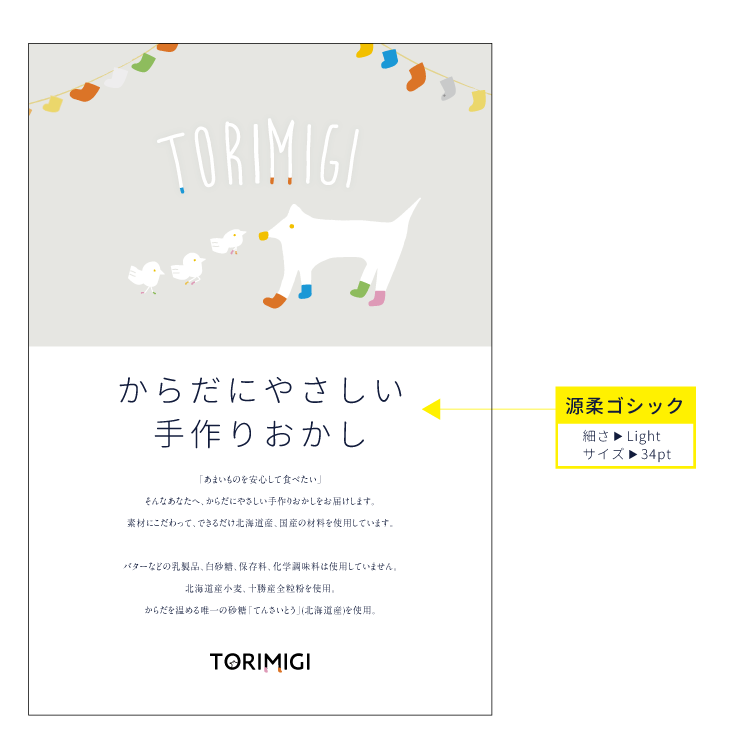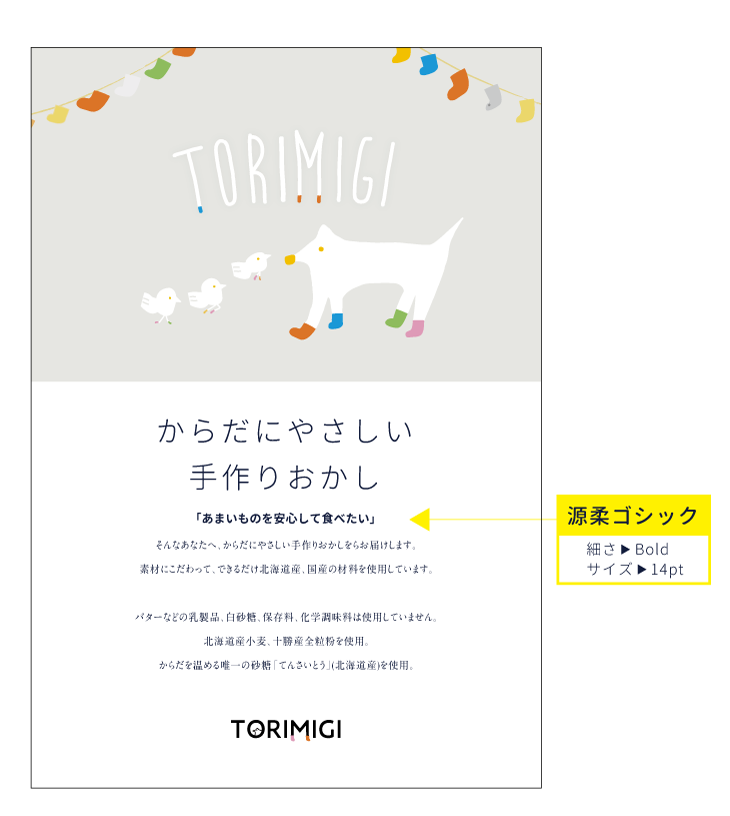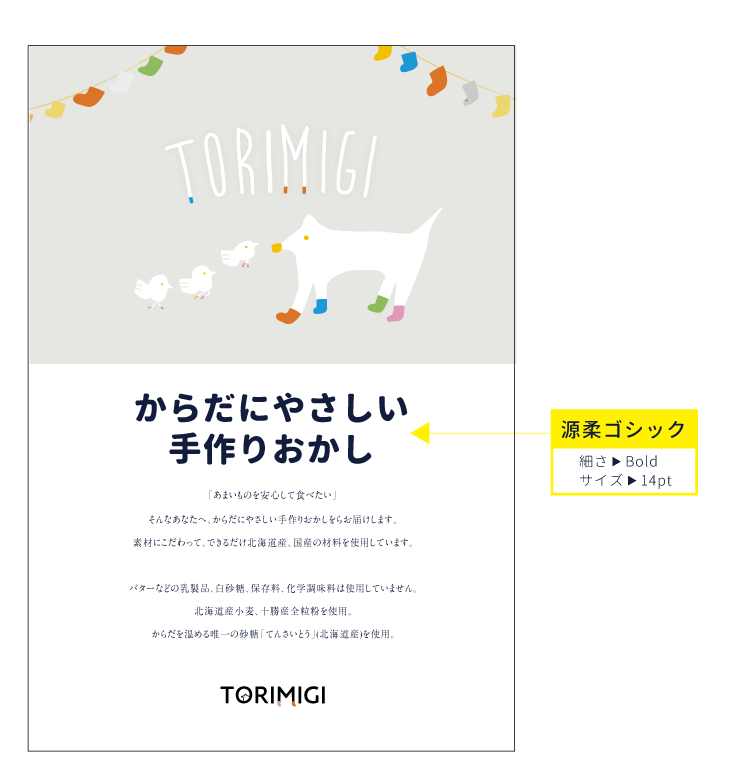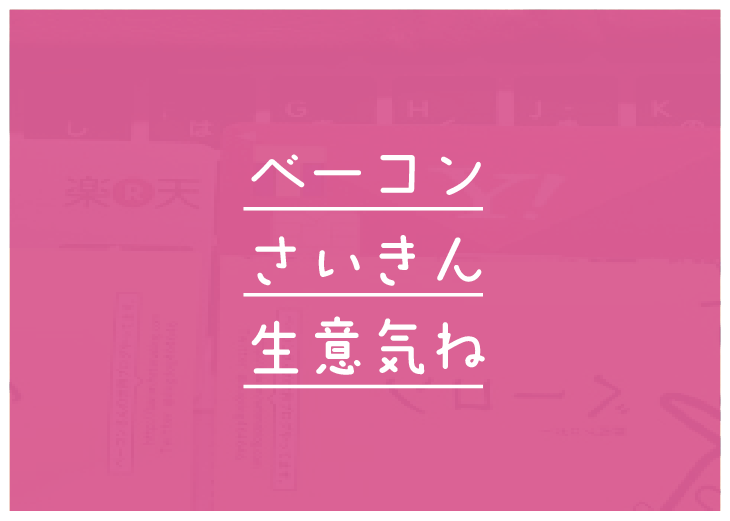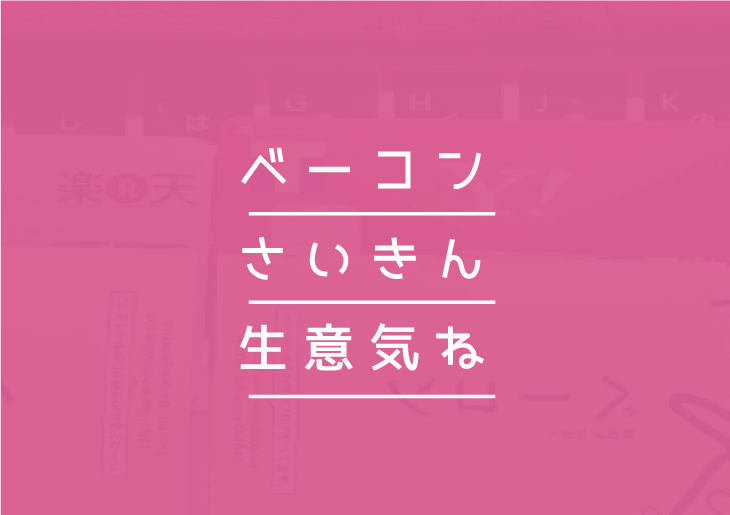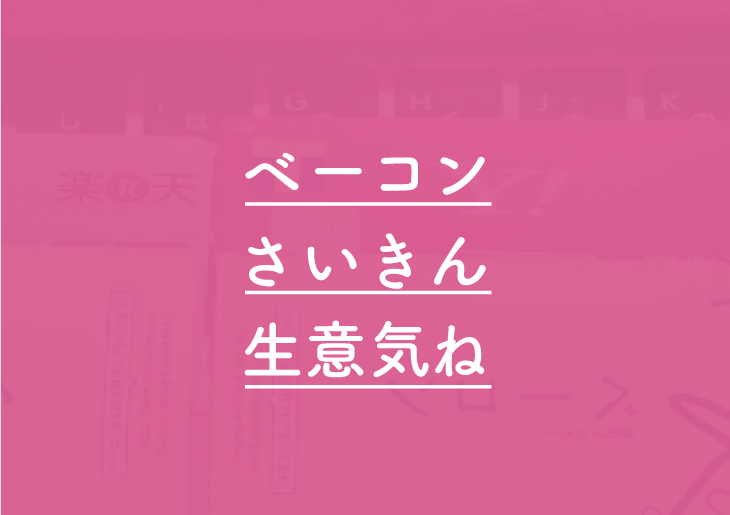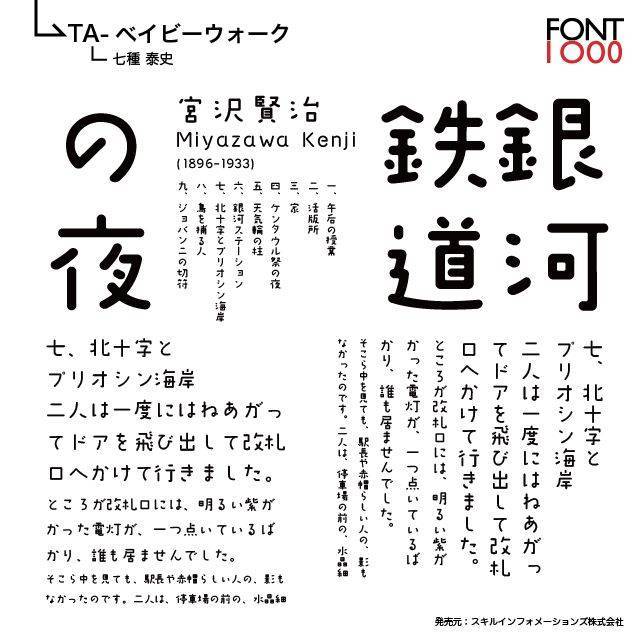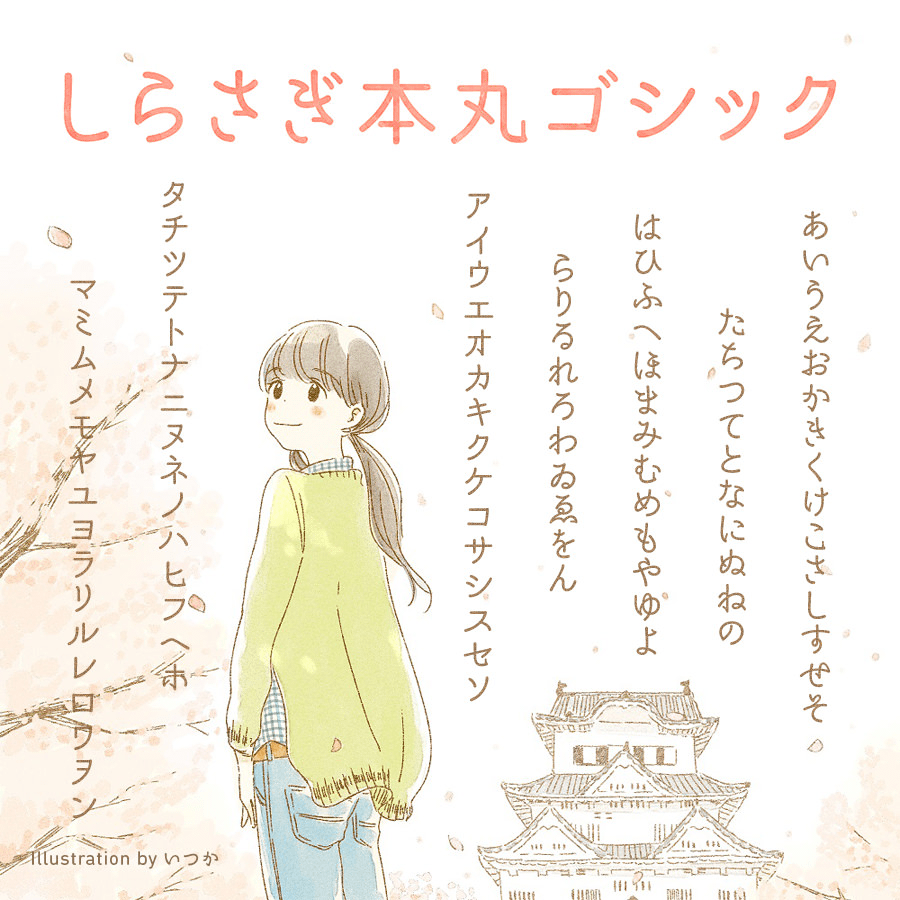
デザイナーのベーコンです
ぼくが普段仕事で使っている、かわいいフォントを紹介します!
どれもデザイン仕事で頼りになる!やつですけど、フォントを選んだ基準はこの2つです
・仕事で使える!
・仕事では使いづらいけどものすごい好き!
どんな場面で使うと上手に使えるのか、デザイナーの目線で解説していきますね!
このルールで行きます!
仕事で頼りにしてる「かわいいフォント」まとめたよ!
①〜④ 有料フォント
1.やまフォント(日本語フリーフォント)
文字の太さがそれぞれバラバラなフォントです、まるで子供の字みたい。
と、、それだけじゃないんです!
こういうような、子供の字のようなフォントって意外とありますが、その中でも飛び抜けていると思うんです。
その理由はこの3つ
1.文字が太いのでタイトルにも使いやすい
2.漢字がある
3.美しいバランス
解説していきます。
1.文字が太いのでタイトルにも使いやすい
子供の字のようなフォントは他にもあるけど、細いものが多いんです。
やまフォントは太いので、タイトルにも使いやすいですね。
2.漢字がある
漢字がないひらがな、かたかなだけのフォントも多いです。
やまフォントは漢字もあります。
3.美しいバランス
やまフォントは文字の太さはバラバラだけど、一つ一つの文字が美しいんです。
明らかにアナログで書かれたアンバランスさが絶妙に気持ちいいのフォントなんです。
やまフォントで作ってみました!
メインのタイトルはやまフォントです。
文字はくずさず、テクスチャなどを入れてみました
使える場面
・商品パッケージ、ポスター・チラシのタイトルに使えます。
・子供の書いた文字を表現する時
・アート感をだしたいとき(美術館のポスターとか)
やまフォントまとめ
下手くそだけど愛しくてたまらないやまフォントの紹介でした。
こういうフォント(文字)好きすぎる。
ポイントは、手書きっぽいけどちゃんとデザインされていることです。この場合は、背景が全面青いことにより「デザインされてる感」が感じられますね
この文字のくずし方も、やまフォントに通じるものがあるよね
美しいなあ
と、ぼくも似たような印象のデザインを、やまフォントで作ってみました!
次は普通の可愛い丸ゴシック?!
いやいや、ただの丸ゴシックじゃないんだよ。
2.源柔ゴシック (げんじゅうゴシック) 日本語フリーフォント
はい、来ました!
一見ただの丸ゴシックですよね。
これの良さが分かる人は、デザイン通だと思います。
このフォントの良さ、ずばり言いますと太さの種類が多いこと、コレとっても大事なことです。
・太さが多いので、様々な表現ができる
非デザイナーほど使ってほしいフォント
デザインを始めたばかりの人や非デザイナーの人が作るデザインって、なにが大事かはっきりさせていないことが多いんです
デザインとは
大事なものに順番をつけて、表現すること
とも言えるんです
つまり、
・大事なこと
・その次に大事なこと
・補足的な表現として伝えるべきこと
これらを整理して表現するのがデザインの大事なポイントなんです。
それを学ぶ前にデザインを作ると大抵こうなります
これも、これも、、これも、ぜんぶだいじ!!!!!!
ごちゃごちゃで、どれも目立たないクオリティの低いデザインが出来上がります。
わかります、未だにぼくやってしまいますからね
大事さの順番をつける具体的な方法
そして、どれが大事さを表現するために必要な方法それが
文字を大きくする
文字を太くする
この2つです。(文字だけで表現する場合ね、画像とか無しで)
この2つを組み合わせると色んなことができます、事例をどうぞ!
※黄色い矢印部分にご注目を!
▼細いけど、文字は大きめで上品なタイトルを演出する…とか
▼太くて力強く、でも主張はしすぎないように(メインタイトルよりは小さめに)
▼太くて、文字も大きめ!なタイトルを作りたいとき
1つのフォントで表現が広がります。
つまりね、
逆に最初から、太さが7種類も入っているフォントがPCに入っていたら日本の資料のレベルが上がるんじゃないかとすら思います。
ここまで聞いたら太さがたくさんあるかわいいフォント、ほしいですか?
丸ゴシック以外も太さの種類のあるフォントをどうぞ
いきなり表現の幅が広がります!
使える場面
タイトルも本文にも対応できます。
メインが普通のゴシックで補足で太めの丸ゴシックを使うとかぼくよくやりますね。
源柔ゴシック まとめ
いきなりあまりにも語りすぎたけど、本当に便利で美しいフォントなのに無料なので是非ダウンロードしてください。
漢字もなんでも入っています。
こういうフォントをダウンロードしておくと、表現したいことをすぐ形にできるのでおすすめです。
3.きりぎりす(有料)
ここ数年、ぼくの中で、1番仕事で使えるフォントです。
お客さんにデザインを見せるとOKが出やすいフォントだと言えます
通常のゴシック・明朝ではないデザイン系フォントだとNo.1に使えます。
・懐かしい感じもするので、仕事のお金を持っている年が上の方にも受け入れてもらいやすい
・若い人にもかわいく受け入れてもらえる(色を付けるとかわいい)
・太いのでタイトルに使いやすい(太いフォントは意外と少ない!)/p>
使える場面
・商品パッケージ、ポスター・チラシのタイトルに使えます。
キリギリスに似たフリーフォント
めもわーる
いかほ ひらがな
どのフリーフォントもひらがな・カタカナのみなんですよね。
契約フォントに入っているベビポップ(もちろん漢字あり)というフォントがキリギリスと同じような印象です
キリギリスまとめ
いまだ現役のうちのエースフォント!
下記のように似た雰囲気の有料フォントも多くあります。
4.ベイビーウォーク(有料)
まっすぐな線が印象的な細いフォントです
女子向けの本の表紙に使えそうです
・都会的な印象
・若いおしゃれ女子
事例も作ってみました
▼例えばブログ記事タイトルに使うのはどうでしょう
▼ちなみにこれがヒラギノフォントだったらこうなります
良い悪いかではなく、だいぶ印象が違うかと思います。
ベイビーウォークの都会感感じられたでしょうか?
おしゃれなEテレの番組感もあるかも…(気づいた?)
ベイビーウォークに似たフリーフォント
ベイビーウォークまとめ
地味で好きなフォントには選ばれづらいフォントですが、たまにこいつにしかできない場面がでて助かっています。
都会的でかわいい女子のフォントです。
5.筑紫A丸ゴシック(有料/Macに入っている)
かわいすぎない丸ゴシック、筑紫A丸ゴシックです。
普通の丸ゴシックより上品なんですよね。
・ゴシック体だとちょっと硬い
・普通の丸ゴシックだとかわいすぎる
そんなときに便利なのが筑紫A丸ゴシックです!
資料や文章を作る時に本文に使っても、違和感もないしおしゃれです。
このツイッター用の画像の上の部分も筑紫A丸ゴシックです
フォントをヒラギノ(Macに入っている)に変えたバージョンも比較として作りました
▼タイトルと本文は丸ゴシックで作った事例
▼さっきの事例をA丸ゴシックバージョンで
下のヒラギノと比べると、A丸ゴシックのひらがなのかわいさが際立ちますね
▼ヒラギノ
筑紫A丸ゴシックに似たフリーフォント
最近のMacには入っているフォントですがWindowsの方のための似ているフリーフォントを探すとするとこちらです。
ほのか丸ゴシック
しらさぎ本丸ゴシック
漢字もあり
しらさぎ本丸ゴシック
いろはモチ
2018年に公開されたフォント、ひらがな、カタカナだけですが漢字は「筑紫A丸ゴシック」を使うとかなり相性がいい。いいね、コレ
きこりフォントに似てるフリーフォント
まるっかなフォント
唯一無二のフォントなので、難しいですが、しいていえばまるっかなフォント。
同じような可愛くて特徴的で太さがあるフォントなので、同じような場面で使えます。
きこりフォントまとめ
とにかく個性が強いフォントです。
使いみちがハマった時は力を発揮してくれることでしょう。
デザインに困ったとき、このフォントが新しい道を開いてくれるかもしれません。
まとめ
まだまだ語りたいことはたくさんあります
もしまだかわいいフォント知りたいよ!という方はあかり、パルラムネ、ベビポップ、すずむし、A1ゴシック、ロゴGをあたりをチェックしていただけると「かわいいフォント」の世界にもっと深く入っていけると思います。
いいフォントを正しい場面で使うとデザインが締まってきます
デザインの雰囲気を感じ取り、デザイン制作に役立ててください。